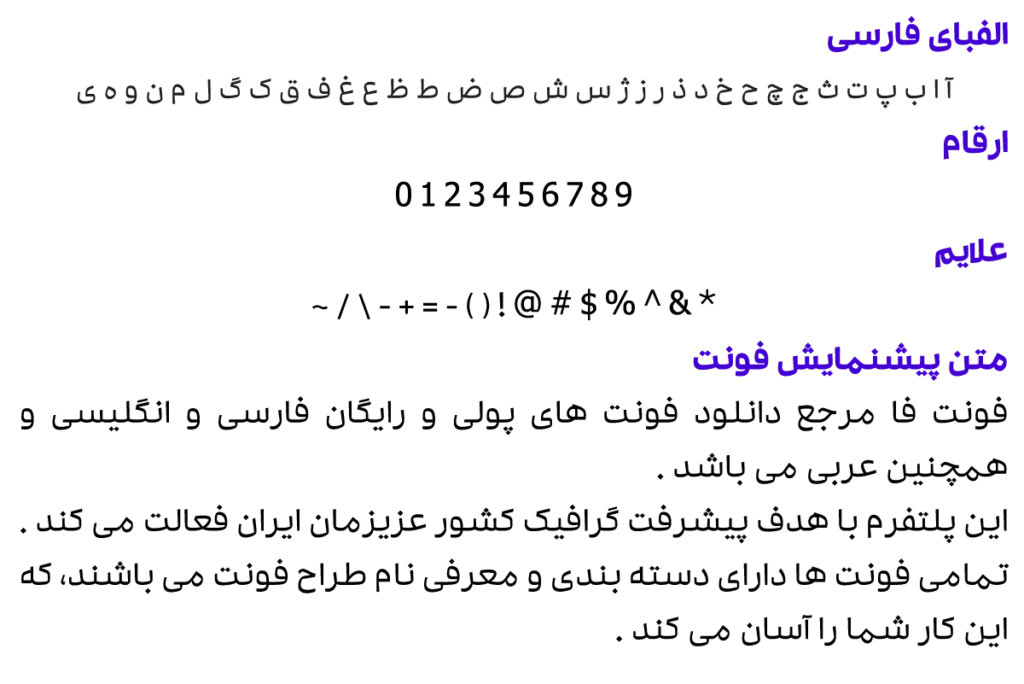
فونت فارسی کارا - SG Kara
توضیحات و معرفی فونت کارا
فونت فارسی کارا ( SG Kara ) از مجموعه فونت های آزاد و برتر می باشد، همچنان نوع فونت عنوان و متن می باشد.
فونت شگفت انگیز و زیبای فوق توسط دامون خانجان زاده در سال 1396 طراحی و ساخته شده است.
تایپ فیس معرفی شده قلم اختصاصی همکاران سیستم که توسط این شرکت بصورت رایگان منتشر شده است.
توضیحات شرکت سازنده در مورد فونت کارا
یکی از عوامل موفقیت استارتاپ ها، توجه به نیازهای کاربران است.
در همین راستا، همکاران سیستم با هدف ارتقا تجربه کاربران نرم افزارهای خود، اقدام به طراحی یک قلم اختصاصی کرده است؛ قلمی که علاوه بر هم‌خوانی با هویت بصری برند، به بهبود خوانایی، کاهش خستگی چشمی و افزایش دقت کاربران در استفاده طولانی مدت از نرم افزار کمک می‌کند.
در طراحی این قلم به جزئیاتی همچون تمایز واضح اعداد، تفکیک پذیری علائم و خوانایی بالا توجه شده است.
این قلم بر سه اصل استوار است:
1. پیروی از هویت مدرن برند
2. تطابق با رسم الخط فارسی
3. برخورداری از ساختار هندسی و قابلیت توسعه برای زبان‌های فارسی‌نویس همچون عربی، کردی، اردو، دری و پشتو
همچنان فونت در 3 وزن نیمه پر رنگ و سبک و معمولی است.